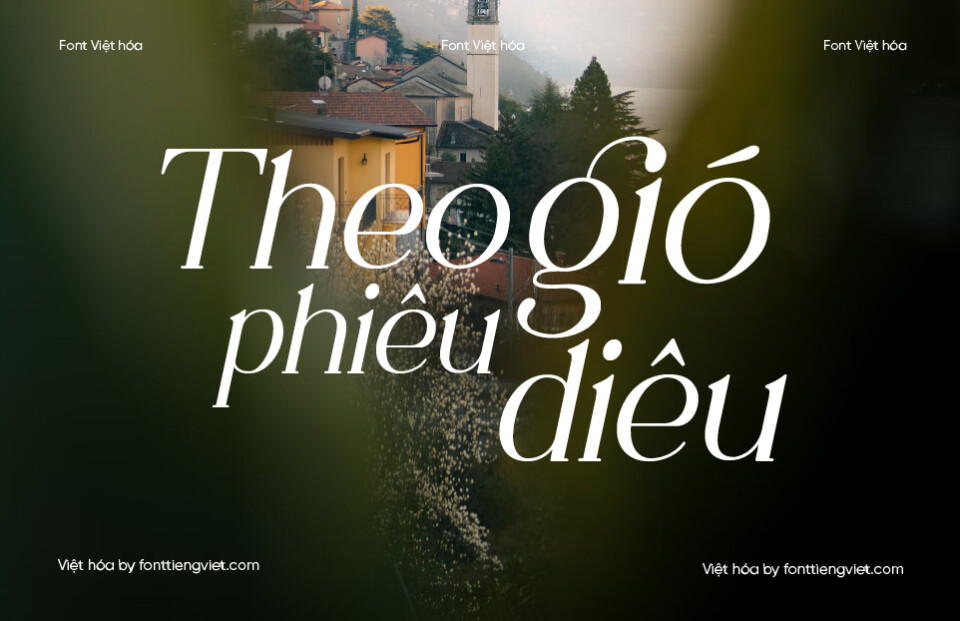
Font Việt hóa 1FTV VIP Wasted Vindey Italic
Giới thiệu về Font Việt hóa 1FTV VIP Wasted Vindey Italic
Trong thế giới thiết kế đồ họa hiện đại, việc lựa chọn một bộ phông chữ phù hợp đóng vai trò quyết định đến linh hồn của tác phẩm. Font Việt hóa 1FTV VIP Wasted Vindey Italic là một trong những lựa chọn hàng đầu dành cho những ai đang tìm kiếm sự kết hợp hoàn hảo giữa nét cổ điển và phong cách hiện đại đầy phá cách. Đây là một bộ Font Miễn Phí chất lượng cao, được đội ngũ chuyên gia tối ưu hóa hoàn toàn cho tiếng Việt, giúp người dùng không còn lo lắng về lỗi hiển thị dấu hay khoảng cách ký tự. Với đường nét nghiêng tinh tế và uyển chuyển, bộ font này mang lại cảm giác phóng khoáng, tự do nhưng vẫn giữ được sự chuyên nghiệp cần thiết cho mọi dự án từ học đường đến truyền thông chuyên nghiệp.
Đặc điểm nổi bật của Font Việt hóa 1FTV VIP Wasted Vindey Italic
Phong cách thiết kế Italic độc đáo
Điểm nhấn lớn nhất của Font Việt hóa 1FTV VIP Wasted Vindey Italic chính là định dạng Italic (chữ nghiêng) mang đậm tính nghệ thuật. Không giống như các phông chữ nghiêng thông thường vốn chỉ dùng để nhấn mạnh nội dung, bộ font này được thiết kế để làm chủ đạo cho các tiêu đề lớn. Các nét chữ có độ dày vừa phải, tạo nên sự cân bằng thị giác cực tốt trên cả màn hình kỹ thuật số và bản in ấn. Điều này đặc biệt hữu ích khi các bạn học sinh, sinh viên muốn tạo ra những trang bìa báo cáo hoặc slide thuyết trình có sức hút mạnh mẽ với thầy cô và bạn bè.
Khả năng tương thích và Việt hóa chuẩn SEO
Một vấn đề thường gặp khi sử dụng các phông chữ nước ngoài là lỗi dấu tiếng Việt như “ă, ê, ơ, ư”. Tuy nhiên, với Font Việt hóa 1FTV VIP Wasted Vindey Italic, mọi ký tự đặc biệt trong bảng chữ cái tiếng Việt đã được hiệu chỉnh tỉ mỉ. Các dấu thanh được đặt ở vị trí chuẩn xác, không bị đè lên nét chữ, đảm bảo tính thẩm mỹ cao nhất. Bên cạnh đó, bộ font này có dung lượng nhẹ, giúp việc cài đặt lên các phần mềm như Photoshop, Canva hay Microsoft Word diễn ra nhanh chóng và mượt mà mà không gây giật lag cho thiết bị.
Ứng dụng thực tế của Font Việt hóa 1FTV VIP Wasted Vindey Italic
Thiết kế ấn phẩm học đường và sáng tạo
Trong môi trường giáo dục, việc trình bày nội dung một cách dễ hiểu và bắt mắt là rất quan trọng. Font Việt hóa 1FTV VIP Wasted Vindey Italic rất phù hợp để làm tiêu đề cho các câu lạc bộ, thiết kế áo lớp hay làm thiệp mời các sự kiện trường học. Phong cách “Wasted” mang chút hơi hướng đường phố nhưng lại được làm mới một cách lịch sự, giúp các bạn trẻ thể hiện được cá tính riêng mà vẫn phù hợp với thuần phong mỹ tục. Ngoài ra, các nhà thiết kế web cũng có thể sử dụng bộ font này để tạo ra các biểu ngữ (banner) quảng cáo đầy ấn tượng và thu hút người xem ngay từ cái nhìn đầu tiên.
Kết luận về bộ font đẳng cấp này
Tóm lại, việc sở hữu một bộ phông chữ đẹp như Font Việt hóa 1FTV VIP Wasted Vindey Italic sẽ giúp bạn nâng tầm giá trị cho mọi sản phẩm thiết kế. Sự tỉ mỉ trong quá trình Việt hóa cùng phong cách thiết kế độc quyền đã biến nó thành một công cụ không thể thiếu trong kho tài nguyên của bất kỳ ai yêu thích sự sáng tạo. Hãy truy cập ngay vào Font Miễn Phí, Font Việt Hóa, Font Việt hóa 1FTV VIP Wasted Vindey Italic để tải về và trải nghiệm những tính năng tuyệt vời nhất. Hy vọng bài viết này đã cung cấp cho bạn cái nhìn chi tiết và hữu ích nhất về bộ font đặc biệt này. Chúc bạn có những tác phẩm thiết kế thật ấn tượng và thành công trong công việc cũng như học tập!